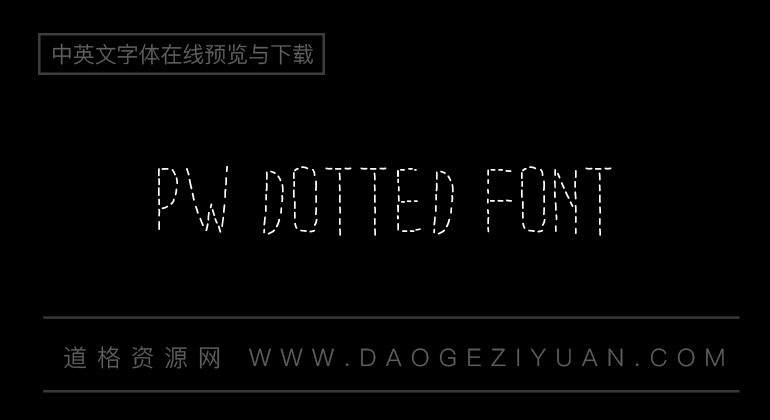
PW Dotted Font 是一款点阵字体,它由一系列的点组成,可以用来构建简单的文字图形,其点阵字体的灵活性使它成为一种流行的字体,可以用来制作各种类型的文字图形,如标题、标签、标识等。PW Dotted Font 字体具有良好的可读性,可以显著提高文字的可视性,同时还具有良好的可扩展性,可以自定义字体大小,以适应不同的应用场景。内容介绍
PW Dotted Font是一款非常不错的手写艺术字体,具有很好的视觉感,适合于文化类的宣传设计、商业类品牌的广告和产品包装设计以及个性化文字排版等较多场景。